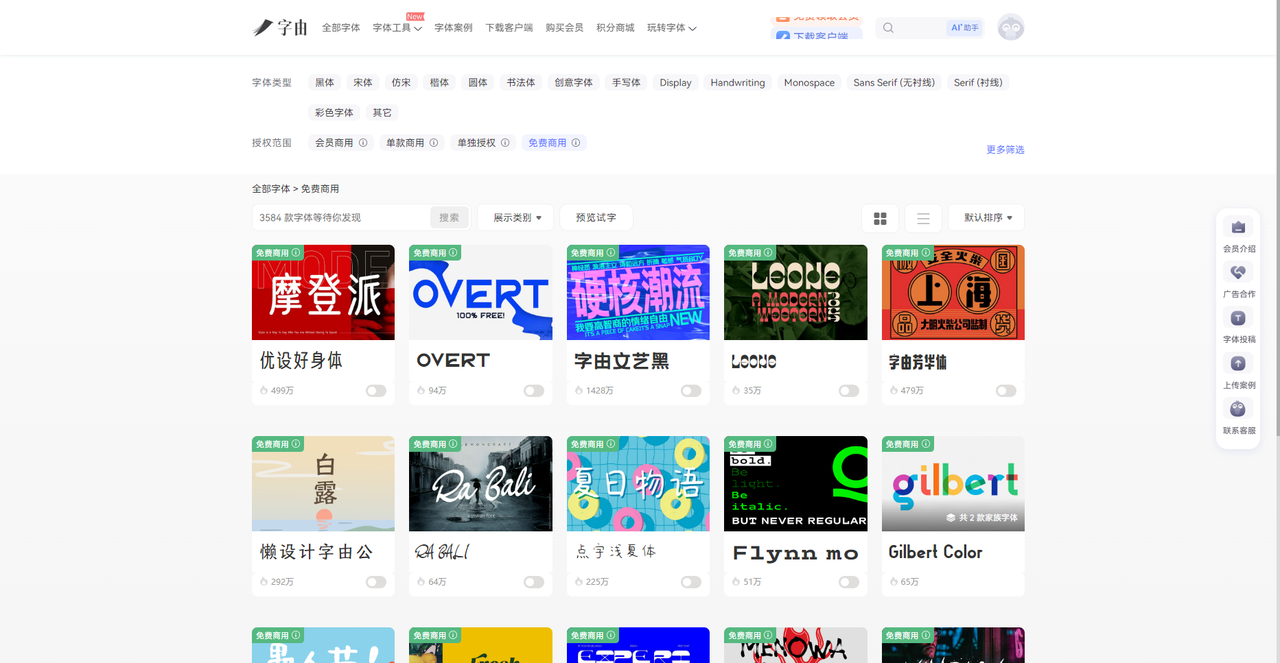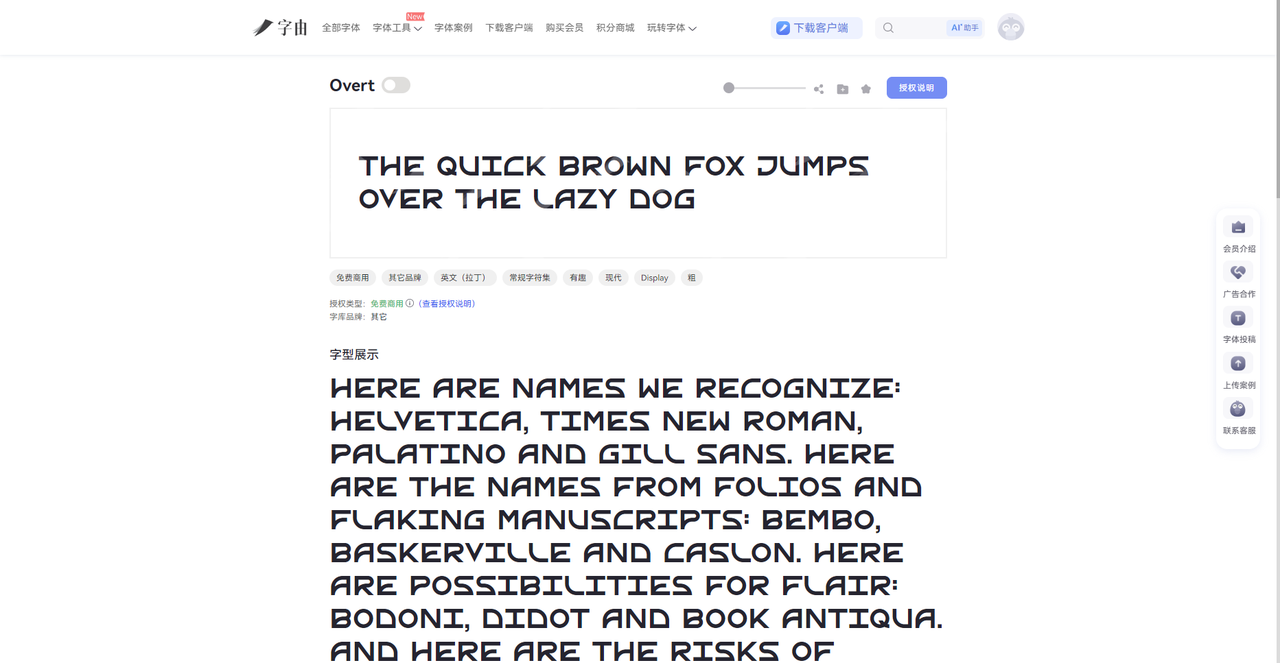
ps字体怎么导入?一篇文章手把手教会你
网上搜索“PS字体怎么导入”,出来的教程乱七八糟五花八门,有的让你去控制面板找你的字体文件夹,也有的叫你怎么安装,有的甚至要麻烦到让你重启电脑。虽然整体上来看步骤不算多也不算难,但是如果每次都要这么折腾的话属实是有点难为人。那么今天的文章我不会和你讲那些老办法,而是要用到一个妙妙工具:字由。仅凭这一个工具基本上就可以解决字体设计和使用的全套流程,来手把手教你怎么导入 PS 字体,不用下载安装包也不用重启软件,点一下就能换字体,接下来就看看怎么具体实操吧!
1、传统字体导入的不便之处
2、主要应用软件:字由
字由,是一个集字体库、字体管理和设计辅助于一体的平台,目前注册用户超2000万,是很多设计师电脑里的必备工具。它把 10500 多款字体打包成一个分类详细的字体库,你不需要一个一个下载安装,打开客户端就能直接在 PS 里调用,而且字体都标注了授权类型,免费商用、会员商用一目了然,再也不用担心版权问题。并且会员也不是强制要求的,大部分免费的字体足够普通用户使用了。
3、用字由导入 PS 字体详细步骤
接下来就是最核心的部分, PS 字体怎么导入?我先说一个结论,用字由的话其实根本不需要“导入”,而是相当于“一键激活”。下面是具体操作步骤:
- 第二步:进入字体库,寻找合适的字体
登录后,点击“全部字体”,进入字体库界面。在筛选栏界面可以帮助你快速找到想要的字体:按类型:黑体、宋体、书法体、手写体、Sans Serif、Serif 等。按授权:点击“免费商用”,目前有3584款免费商用字体,可以放心用。按热度:每款字体右下角有使用次数,可以优先选热度高的。
- 第三步:预览字体效果
点击感兴趣的字体,进入预览界面,不用下载就能知道这款字体适不适合。
- 第四步:一键替换到PS
打开 PS ,新建或打开一个设计文件,用文字工具输入一段文字,选中这个文字图层。再回到字由客户端,找到你刚才看中的字体,直接点击它。神奇的事情发生了:PS里的文字瞬间切换成该字体,完全不需要重启软件,也不需要任何安装过程。
整个流程下来,试一款字体只要1秒钟。这才是ps字体怎么导入的最优解——根本不用导入,直接调用。
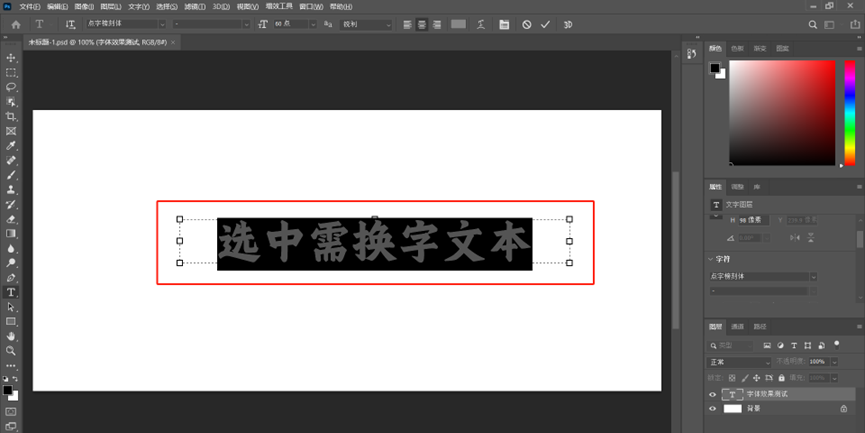
4、推荐几款热门字由网站内字体
- 字由文艺黑(1428万次使用):热度最高的字体之一,既有黑体的稳重,又带一点手写感,适合做标题、海报主视觉,视觉冲击力强。
- 优设标题黑(1044万次使用):优设团队出品,字形方正有力,适合做醒目标题、 banner 字,用在电商设计、活动海报上效果很好。
- 优设字由棒棒(823万次使用):圆润可爱的风格,适合儿童、美食、萌系主题的设计,热度很高,说明很受欢迎。
- 阿里妈妈数黑(560万次使用):阿里妈妈出品的免费商用字体,数字和黑体结合,带有科技感,适合互联网、科技类设计。
- 江西拙楷(538万次使用):手写楷书风格,带着朴拙的手工感,适合国风、文创、书法类设计。
- 思源黑体 Medium(535万次使用):经典的开源字体,字重适中,适合正文排版和 UI 界面,百搭实用。
- 优设好身体(499万次使用):字形方正饱满,适合正文排版和简洁标题,做画册、公众号配文很好用。
除了这些还有阿里妈妈东方大楷、HarmonyOS Sans、钉钉进步体等精品字体值得下载,并且这些字体都可以通过字由一键应用到 PS、AI、Figma 等软件里,不需要下载安装。
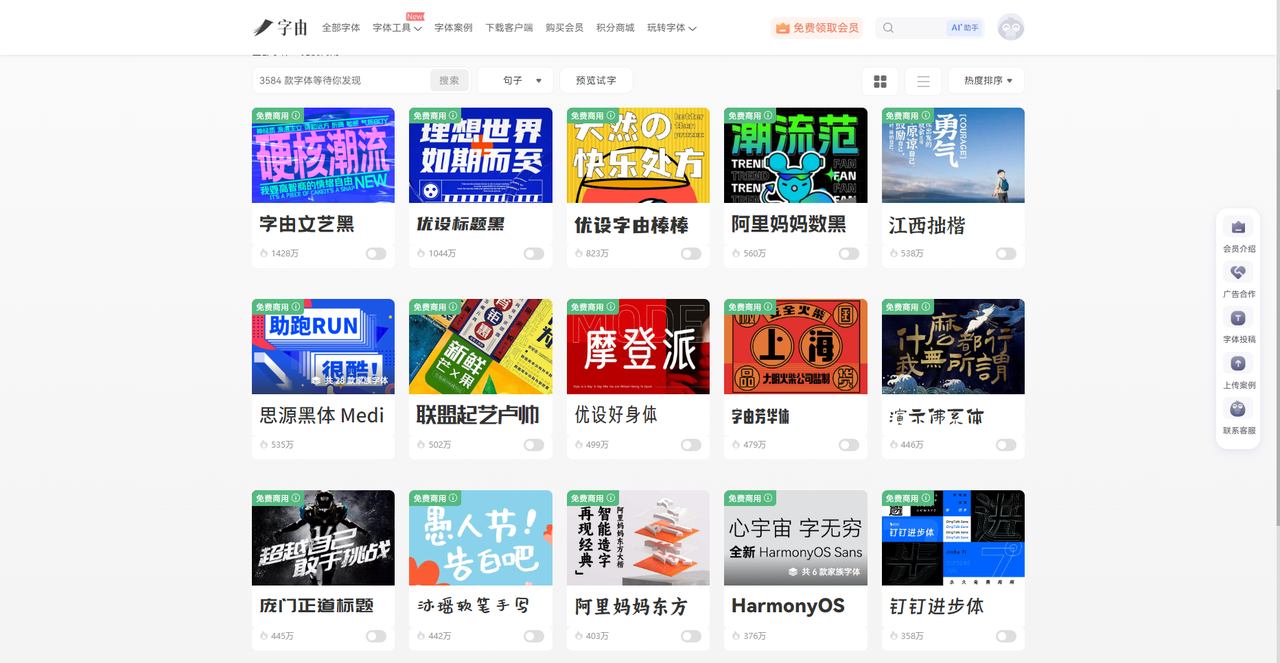
5、字由其他实用功能推荐
最主要的是字由并不是一个单纯的字体网站,它还有很多实用的功能:
- 个人云字库:你可以把本地自己收藏的字体上传到字由的云端,换设备登录账号后直接激活使用。再也不需要用U盘拷来拷去,也不用担心电脑坏了字体丢失。
- AI 智能工具:包括AI 识字、AI 擦除、AI 配字等非常实用的工具